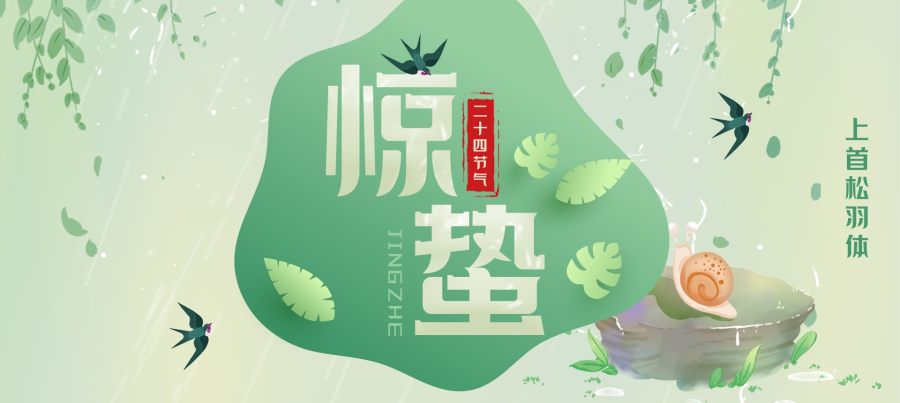
上首松羽体,简体中文约6763字,字形是借鉴了弯刀其独特曲线和力学原理,字体的每个笔画都沿用了其特点;横笔的突出梯形角代表着稳重握柄,竖笔的月牙代表着皎洁弯月的刀身,转折的部分则以刀尖加以装饰,整体着重表现了字体的独特之处,使字体增加了其审美性及文化性,适用于搭配标志、广告标语、商业广告等高端属性。